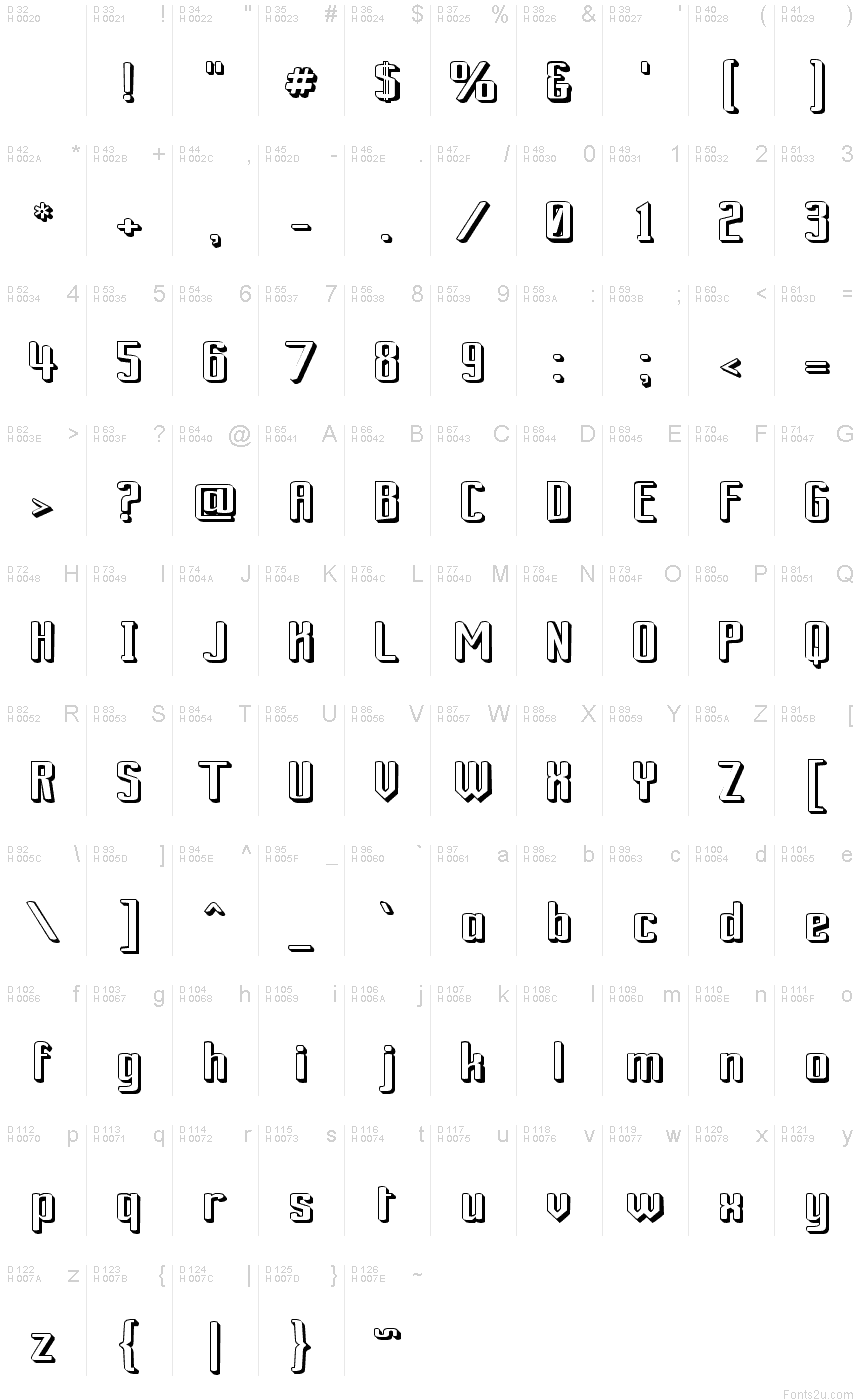
Ardour 3D من تصميم Graham Meade و Andreas Höfeld هو خط عرض (display) مجاني بلمسة ريترو تفرض حضورها بقوة. تتميز الحروف بكونها سميكة ومربعة مع ظل أسود عميق، مما يمنح كل كلمة تأثيرًا ثلاثي الأبعاد بارزًا يشبه تصاميم أجهزة الألعاب القديمة وشعارات السبعينيات الجريئة. التباين الإيقاعي بين المنحنيات والحواف الحادة يضفي حيوية على الخط، بحيث تبدو الكلمة الواحدة كشعار متكامل.
مع Ardour 3D، ستجعل العناوين والملصقات وعناوين الألعاب والنشرات وتصاميم التغليف تبدو وكأنها تقفز من الصفحة. هذا الخط المجاني يتألق عند استخدامه بأحجام كبيرة، حيث تأخذ الخطوط الخارجية والظلال مساحة كافية للبروز. نسّقه مع خط "سان سيريف" (sans serif) بسيط وهادئ للنصوص الفرعية، وستحصل فوراً على هوية بصرية بلمسة كلاسيكية مع وضوح تام في القراءة.